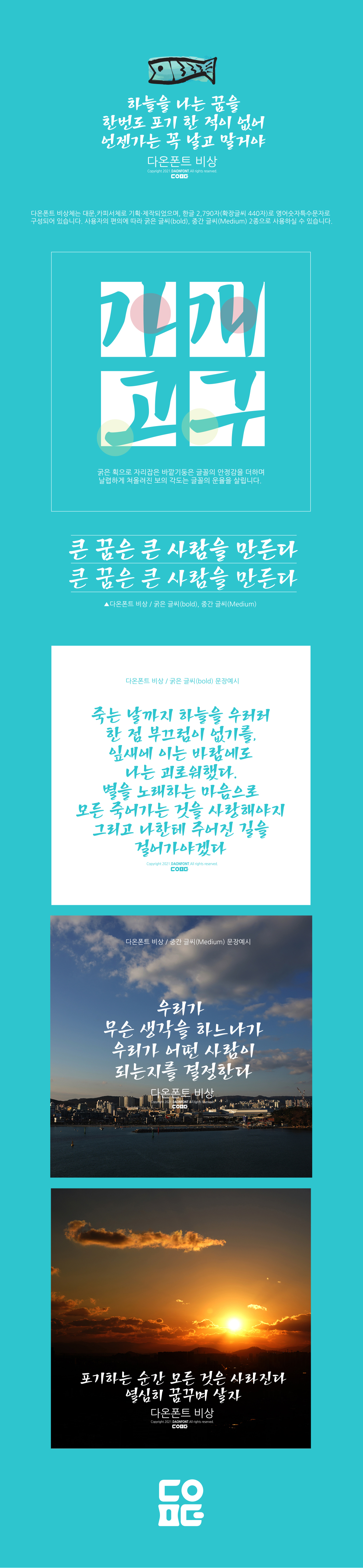
다온폰트 '비상'(2종)이 업데이트 되었습니다.
다온폰트 '비상'은 대문 및 카피형 서체로 기획 제작 되었습니다.
한글 2,790자(기본글씨 2,350자 + 확장글씨 440자)와 영어,숫자,특수문자로 구성되었으며,
자소굵기에 따른 굵은글씨, 중간글씨 2종으로 제작되었습니다.